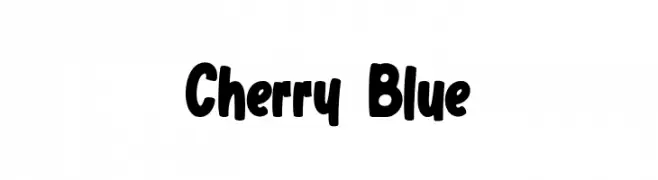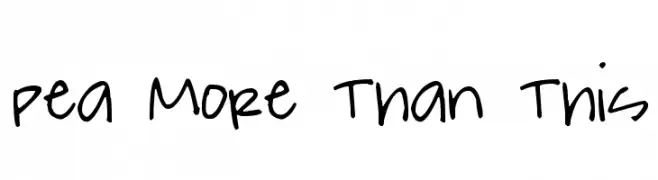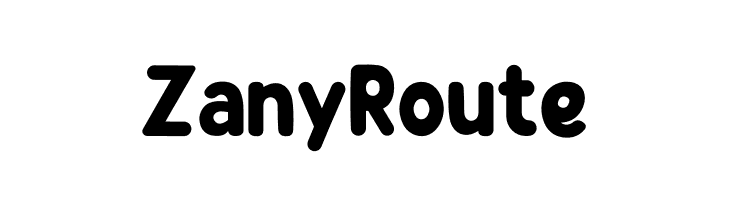
Добро пожаловать в раздел Топ шрифтов — здесь популярность встречается с качеством. Это самые скачиваемые и используемые шрифты нашего сообщества за этот год. Если нужны надежные варианты для логотипов, сайтов или соцсетей — начните отсюда.
Каждый топ‑шрифт отличается балансом, читабельностью и универсальностью. Здесь есть современные гротески, изящные скрипты, винтажные антиквы и минималистичные дисплейные семейства. Если не знаете, с чего начать, раздел «Топ» — ваш короткий путь к проверенной типографике.
A serif typeface combining traditional and modern elements with sharp serifs and strong vertical stress.
A thin, modern sans-serif font with a stamped texture and minimalist design.
A playful and informal handwritten font with a casual vibe.
A modern, clean sans-serif font supporting the Ethiopic script with excellent readability.
A high-contrast, elegant font with dramatic serifs and curves.
A bold, playful font with rounded edges and a friendly, approachable style.
An artistic script font with flowing, interconnected letters and whimsical flourishes.
A playful, casual handwritten font with a dynamic and friendly style.
Какие шрифты в топе прямо сейчас?
Дизайнеры любят Once Upon A Dream, Grenze Regular, Austral Sans Stamp Thin, Pea Christen and Noto Sans Ethiopic Regular за чистые формы и широкий спектр применения — от фирменного стиля до лендингов и постеров.